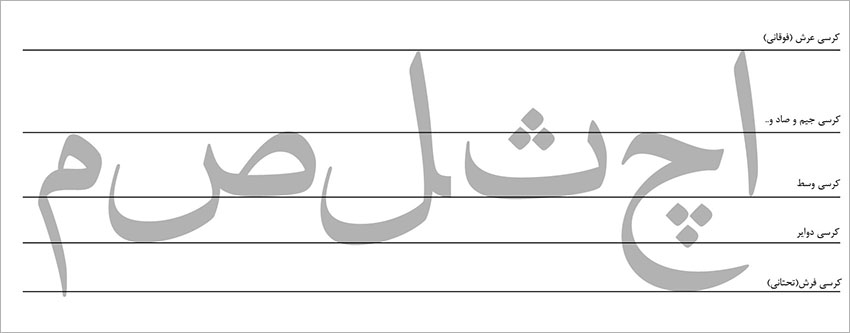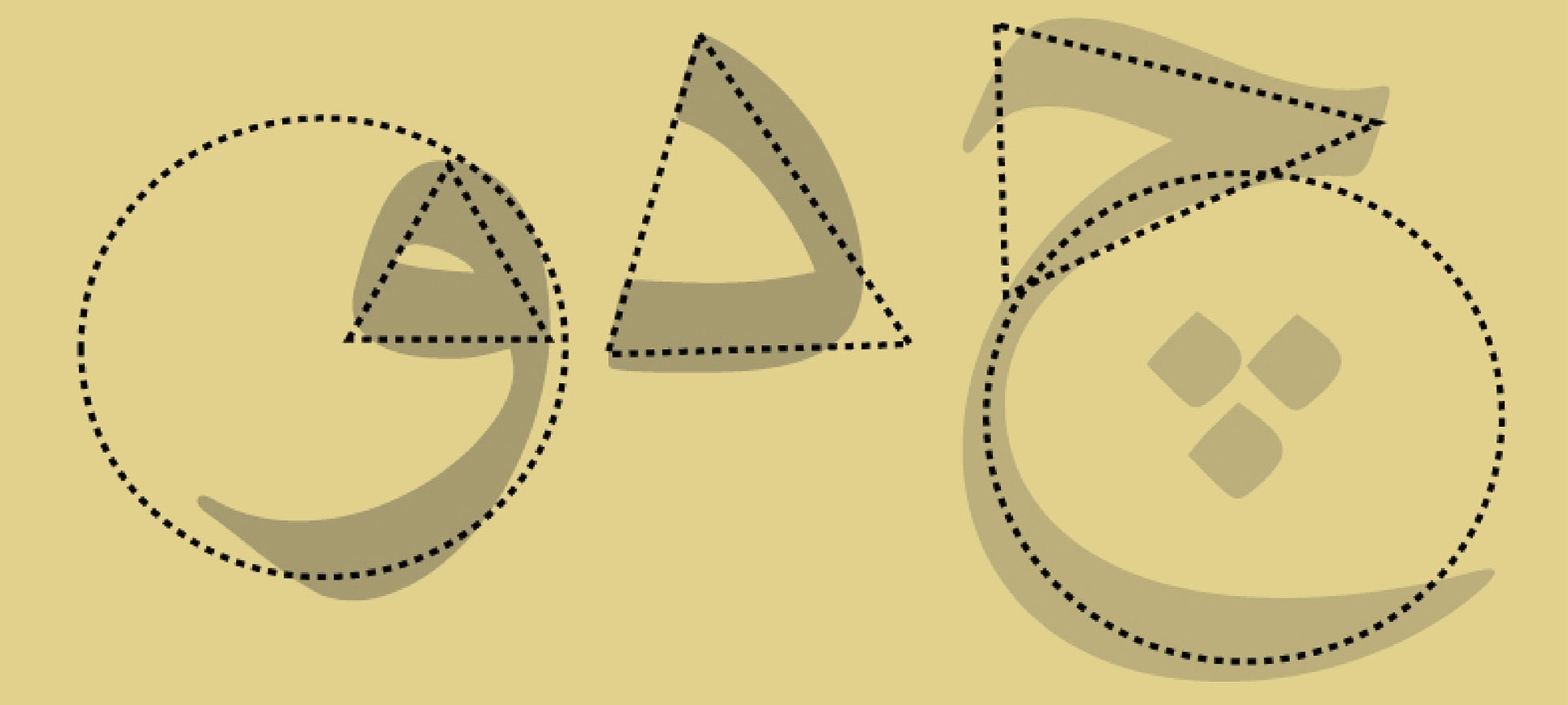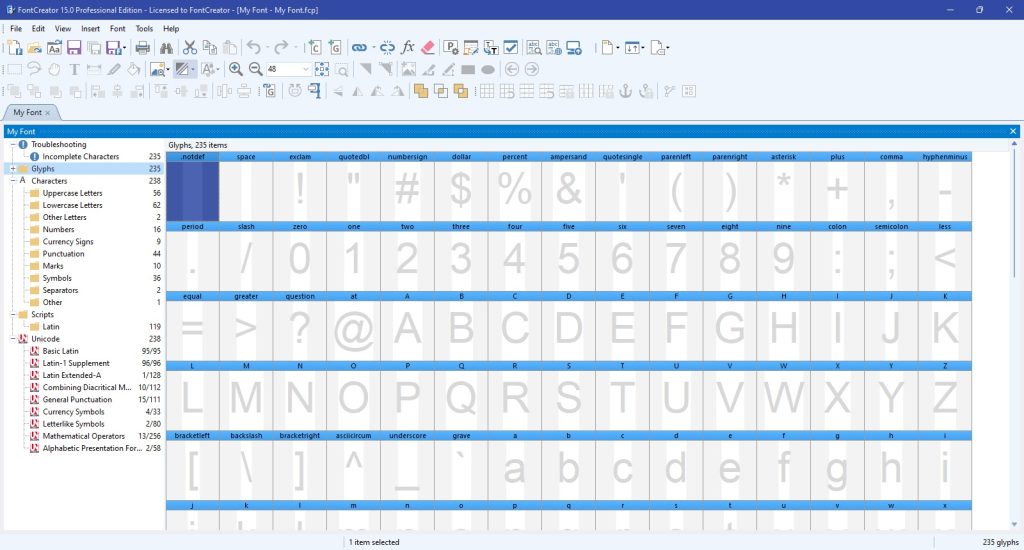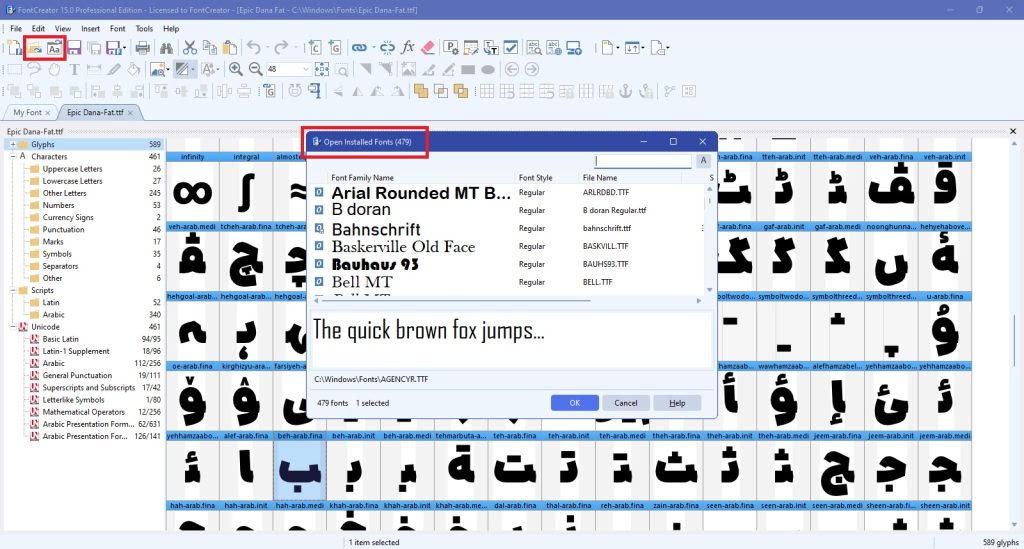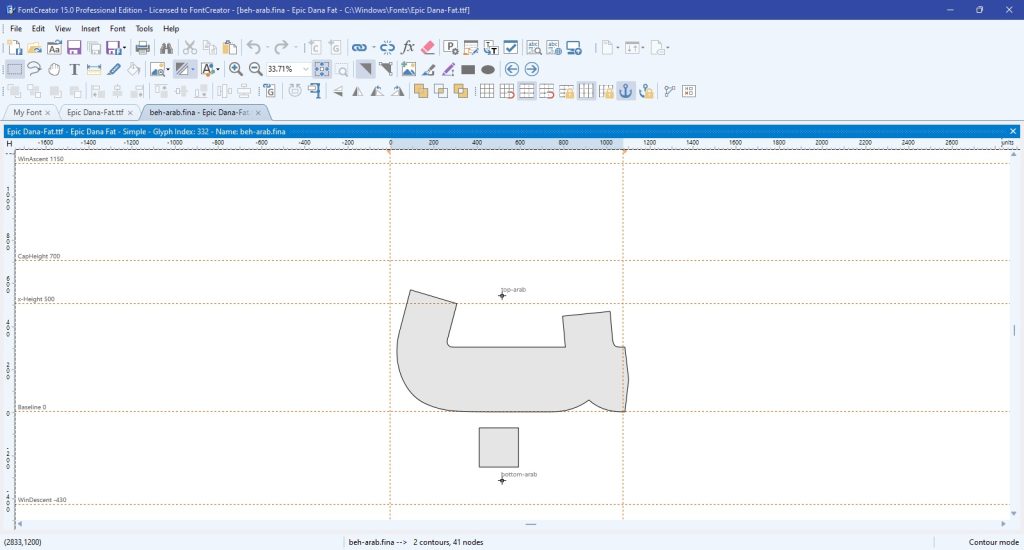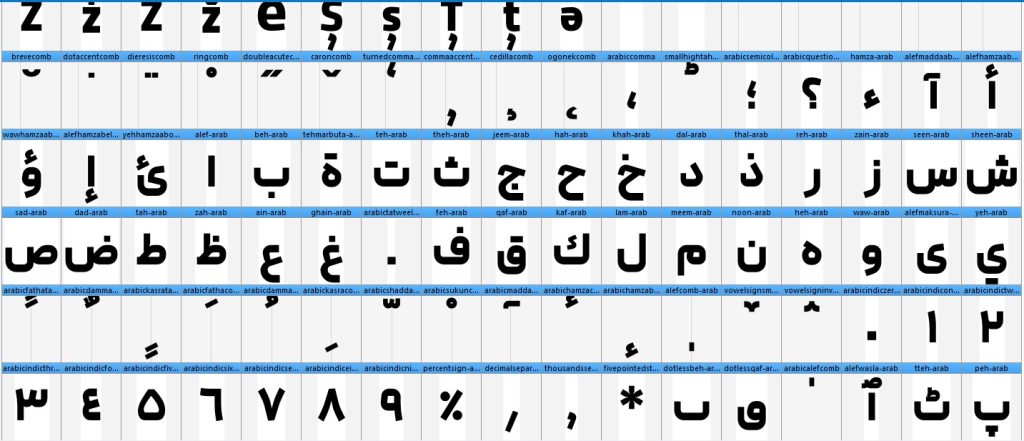
آشنایی با طراحی فونت
طراحی و ساخت فونت
اصطلاحات کاربردی طراحی فونت
آموزش طراحی و ساخت فونت یک کار کاملا تخصصیه ولی ما میخوایم شمارو با کلیت این حرفه توی این مقاله آشنا کنیم. قبل از اینکه وارد آموزش بشیم ، لازمه با چند اصطلاح کاربردی آشنا بشیم:با ما همراه باشید
تایپو گرافی(نویسه نگاری)
تایپوگرافی به مجموع کارهایی که یک طراح بر روی حروف الفبا جهت  زیبا سازی و دادن هویت بصری به یک پروژه مثل (پوستر ، بروشور،تیتراژ فیلم و…) انجام میدهد ، می گوییم.
گلیف: (glyph)
گلیف ها اجزای تشکیل دهنده ی یک قلم(فونت) هستند. به عبارتی دیگر ،یک فونت از مجموعه ای از کاراکترها، سمبل ها و حروف تشکیل شده است و از طرفی هر کاراکتر دارای حالت های مختلفی است برای مثال حرف ب دارای چند حالت (تنها، چسبان،اول و…) میباشدو این حالات مختلف یک کاراکتر را گلیف می گویند.
خط کرسی
خطی است فرضی ،که به منظور قرار گرفتن حروف در یک طراز مشخّص به کار میره و تعداد اون توسط طراح ، تعیین میشه.هرگونه تغییر در اندازه و تعداد خط کرسی از عوامل تاثیرگذار در ساختار کلی تایپ فیس است.
طراحی و ساخت تایپ فیس
مرحله اول: طراحی دستی روی کاغذ
اولین گام واسه آموزش طراحی و ساخت فونت، طراحی دستی اون روی کاغذه وهرچقدر طراحی دستی ، دقت و ظرافت بیشتری داشته باشه نتیجه کار بهتر و جذّاب تر از آب در میاد.
مرحله دوم :پیاده سازی طرح به وسیله یک نرم افزاروکتوری
توی این مرحله باید طرح خودتون رو به وسیله یک نرم افزار وکتوری مثل (کورل ویا ایلوستریتور) به یک فایل وکتوری تبدیل کنیم .دلیل استفاده از نرم افزارهای وکتوری ، عدم افت کیفیت در اندازه های  بزرگ میباشد.
مرحله سوم: ساخت فونت به وسیله نرم افزارهای طراحی فونت
توی این مرحله شما باید حروف طراحی شده رو  تبدیل به یک فونت کنید.
نرم افزار های وکتوری برای ساخت فونت
مرحله سوم: ساخت فونت به وسیله نرم افزارهای طراحی فونت
برای این کار نرم افزار های زیادی وجود دارن که 5 مورد از بهترین نرم افزار ها رو به شما عزیزان معرفی میکنم.
1-نرم افزار فونت لب استودیو(Fontlab Studio)
2-نرم افزار فونت کریتور(font creator)
3-نرم افزار فونت گرافر(font grapher)
4-نرم افزار گیلیفس(Glyphs)
5-نرم افزار روبوفونت(robofont)
نرم افزار های طراحی و ساخت فونت
ویرایشگر فونت کریتور (font creator ) یکی از بهترین و شناخته شده ترین نرم افزارها در حوزه ساخت و ویرایش فونت است .که با توجه رابط گرافیکی نسبتا ساده گزینه مناسبی برای افراد مبتدی به شمار میرود.
بعد از باز کردن نرم افزار ،صفحه ای مطابق شکل زیر برای شما باز میشه .
نرم افزار فونت کریتور(font creator )، به شما این امکان را می دهدتا هم بتوانید فونت بسازید و هم فونت های نصب شده بر روی سیستم را ویرایش کنید .
برای وارد کردن فونت به نرم افزار File / Open Installed Font را میزنیم سپس لیستی از فونت های نصب شده بر روی ویندوز به نمایش  درمی آید. یکی از فونت های فارسی را انتخاب کنید.
ساخت فونت font creator
آشنایی اولیه با اجزاء فونت
همانطور که می بینیدهر حرف داخل کادر مخصوصی قرار گرفته که به آن گلیف می گوییم.
هر فونت در کمترین حالت از 200گلیف تشکیل شده است .
دلیل زیاد بودن تعداد گلیف ها در زبان فارسی این است که هر حرف در زبان فارسی از چند حالت (اول  میانپاره ،آخر چسبان و آخر تنها تشکیل شده و باید تک تک اونهارو به صورت جداگانه طراحی کنید.
تعدادگلیف ها در فونت هایی که از زبان های (کوردی ،عربی،انگلیسی و…)پشتیبانی میکنندو برای بعضی حروف حالت های جایگزین دارند،بیشتر است .مثلا فونت آهنگ با دارا بودن960گلیف ، یک تایپ فیس کامل محسوب می شود.
با کلیک بر روی هر کدام از حروف پنجره ی جدیدی باز میشه که در آن میتوانید هر یک از حروف رو ویرایش کنید و یا آن را حذف و طرح خودتون  رو جایگزین کنید.
بعد از اینکه هر حرف را در Glyph مخصوص خودش و در مکان صحیح نسبت به خطوط Base Line و Bearing Line قرار دادید باید نام فونت خود را بنویسید تا به عنوان فونت جدیدی در ویندوز شناخته شود.
برای نوشتن نام فونت از منوی Font گزینه Properties را بزنید و روبروی Font Family نام فونت را بنویسید .
برای وارد کردن حرف طراحی شده مطابق تصویر روی گزینه import image کلیک کنید و فایل خود را وارد کنید
حالا برای استفاده از فونت باید از آن خروجی بگیریم .برای خروجی گرفتن از فونت از منوی File روی گزینه Export Font as کلیک کرده و فرمت دلخواه خود را انتخاب کنید
در پایان باید این نکته رو بگم که آموزش طراحی و ساخت فونت یک کار تخصصی هست و به تخصص نیاز داره
در این مقاله فقط سعی شده تا افرادمبتدی که به طراحی و ساخت فونت علاقه مند هستند با کلیت این کار آشنا بشن .